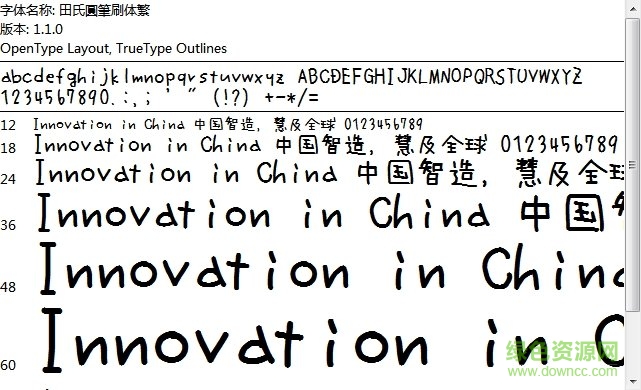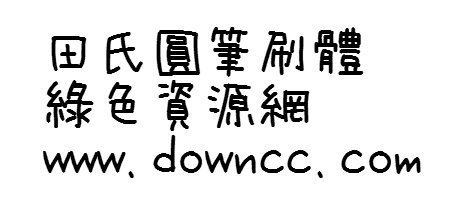
田氏圓筆刷體簡(jiǎn)繁合集
田氏圓筆刷體簡(jiǎn)體是一款田氏系列的筆刷系列字體,比細(xì)筆刷體更顯厚重、比方筆刷體更顯圓潤(rùn),形態(tài)優(yōu)美,能滿足平面設(shè)計(jì)的多種需要,需要的朋友就來(lái)綠色資源網(wǎng)體驗(yàn)吧!
田氏圓筆刷體繁體特色
田氏圓筆刷體暫只推出繁體版,且需要在繁體狀態(tài)下方可正常顯示文字內(nèi)容,可用于繁體文字的包裝設(shè)計(jì)、海報(bào)設(shè)計(jì)、藝術(shù)設(shè)計(jì)等諸多領(lǐng)域!
田氏圓筆刷體簡(jiǎn)體
田氏圓筆刷體暫僅有繁體格式,字體線條有點(diǎn)卡通風(fēng)格,整體效果卻非常出眾,可廣泛應(yīng)用于平面設(shè)計(jì)、廣告設(shè)計(jì)、報(bào)紙雜志、正文標(biāo)題等領(lǐng)域。